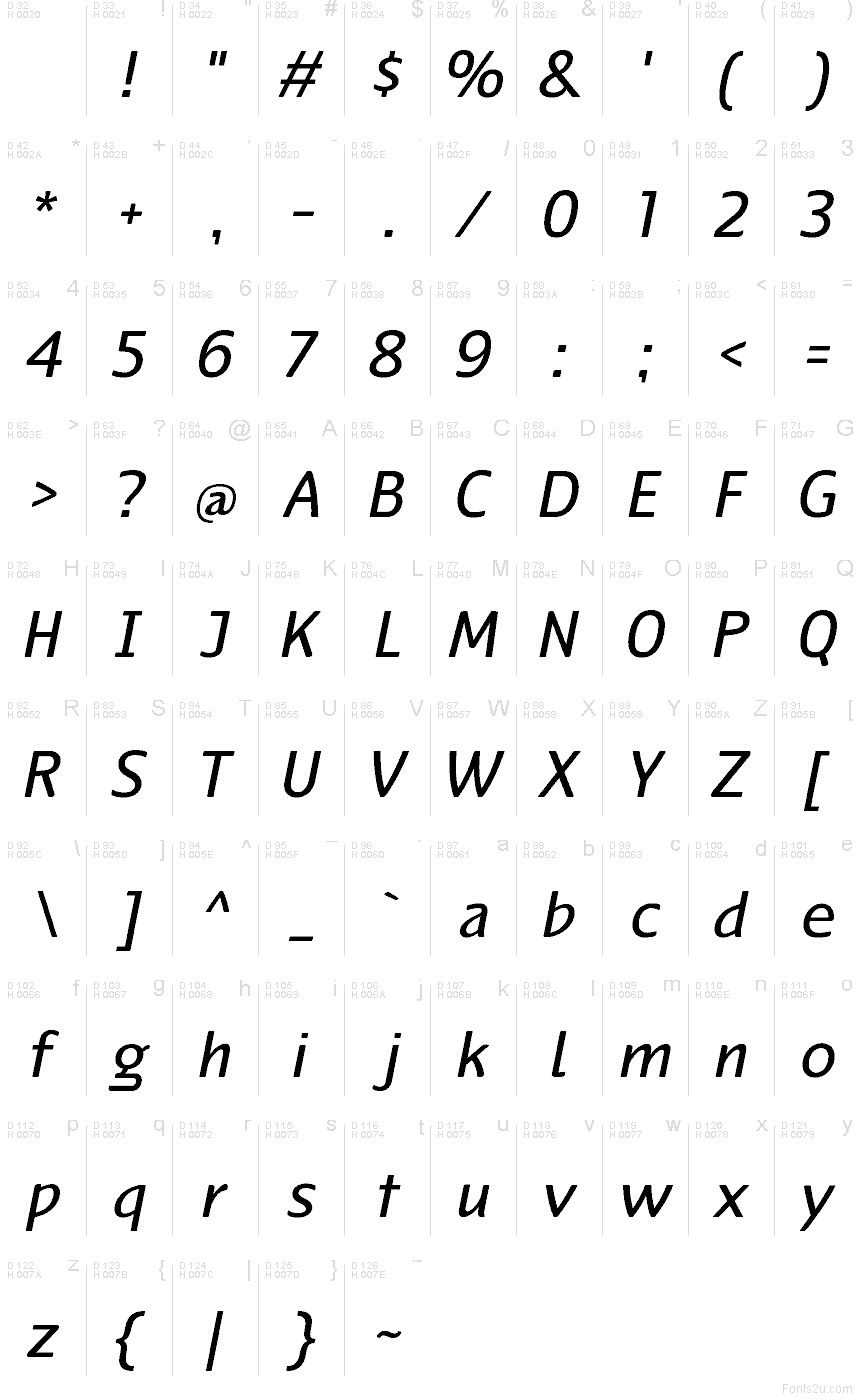
Kinoble, da Jehoo Creative, é uma fonte sem serifa itálica gratuita com um ritmo moderno e fluido, e um leve toque caligráfico. As letras inclinam-se para a frente com traços amplos e confiantes, enquanto as formas arredondadas e as junções suaves mantêm um estilo descontraído em vez de severo.
Adapta-se perfeitamente a branding, títulos editoriais, lookbooks de moda, promoções de apps e design de embalagens, onde um pouco de movimento ajuda as palavras a ganhar vida. Como fonte gratuita, Kinoble também funciona muito bem em títulos curtos, capas e esboços de logotipos, já que o seu desenho inclinado e arredondado confere uma dinâmica rápida, mesmo a palavras simples.